12款日式和风英文字体合集
这套字体汲取了日本传统艺术、书法和设计的美学精髓,将其巧妙地融入英文字母的形态中。每一款字体都展现了不同的日式美学风格,从优雅的书法笔触到简洁现代的设计灵感。无论是用于标题、引用还是文本装饰,都能找到最合适的字体。
Amanojaku
一款融合了传统日式手绘毛笔笔触与现代风格的字体,适用于各种需要强烈视觉冲击的项目。
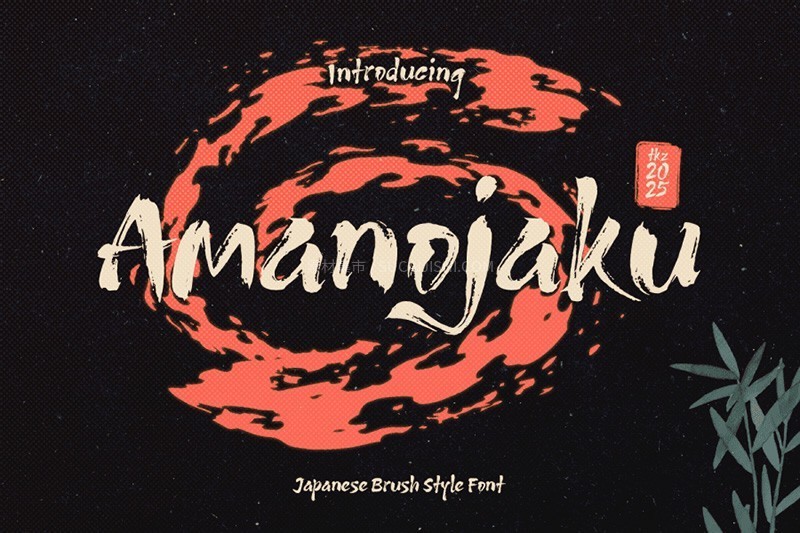
Zyukiharu
一款独特的日式书法风格英文字体。它将东方书法的流畅笔触和艺术感融入英文形态,为您的设计带来一种独特的视觉美感。
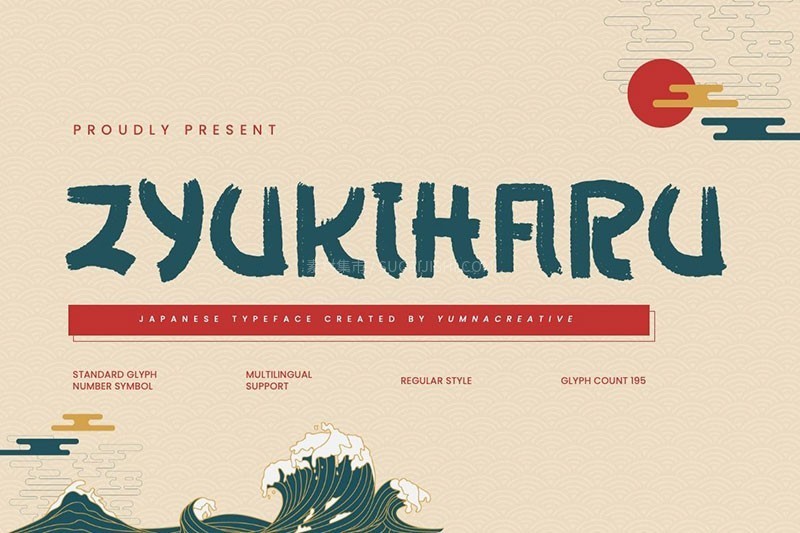
Kotaru
一款巧妙融合了时尚现代设计与传统日式美学的现代日式字体。它旨在打造多功能且易于阅读的排版体验。Kotaru 拥有三种独特的风格——常规、拉伸和轮廓,非常适合各种创意项目,例如徽标、品牌、邀请函、海报、标题、社交媒体等等。
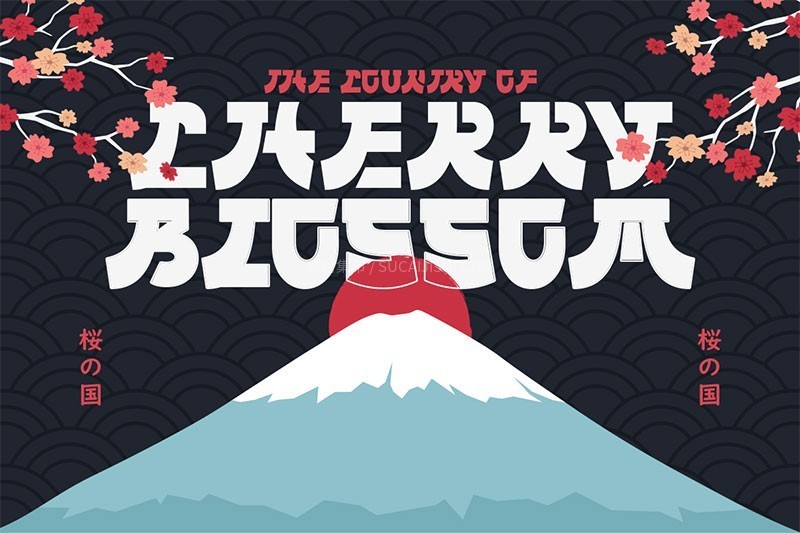
Osake
一款独具艺术价值的毛笔字体,笔触自然流畅,能为您的品牌、菜单、宣传品等增添 authentic(正宗)的日式韵味。
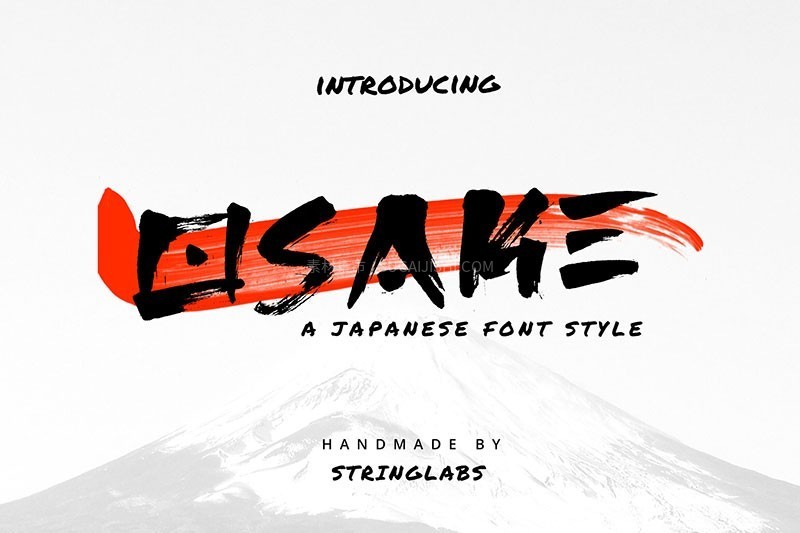
Yokai Game
一款厚重且粗犷醒目的日文字体,其灵感源自传统日式美学与大胆的当代设计。这种独特的融合使其非常适合用于游戏、动漫主题项目、漫画以及电子游戏标题。
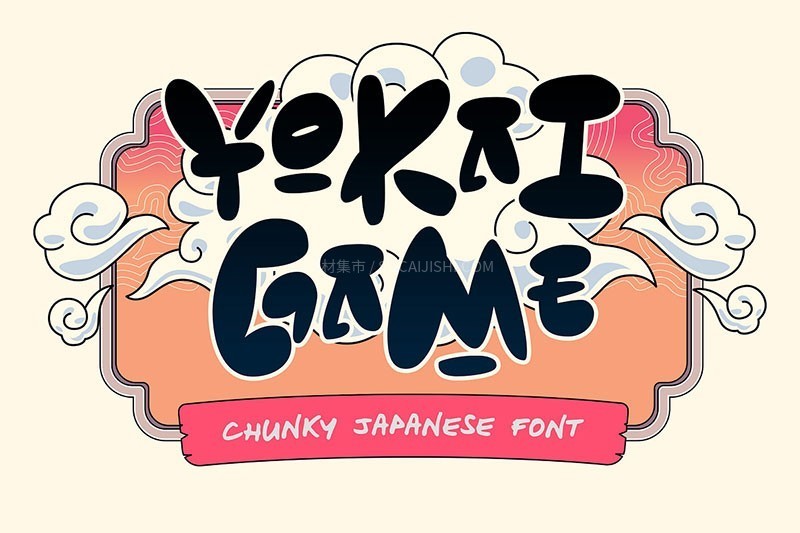
Kawara
一款融合了日式美学的英文字体,专为希望创作日语主题或亚洲风格项目的非日语用户打造。它能让您的标识、食品横幅、品牌形象、海报、电影/书名以及引言等内容更加华丽、强劲、醒目。
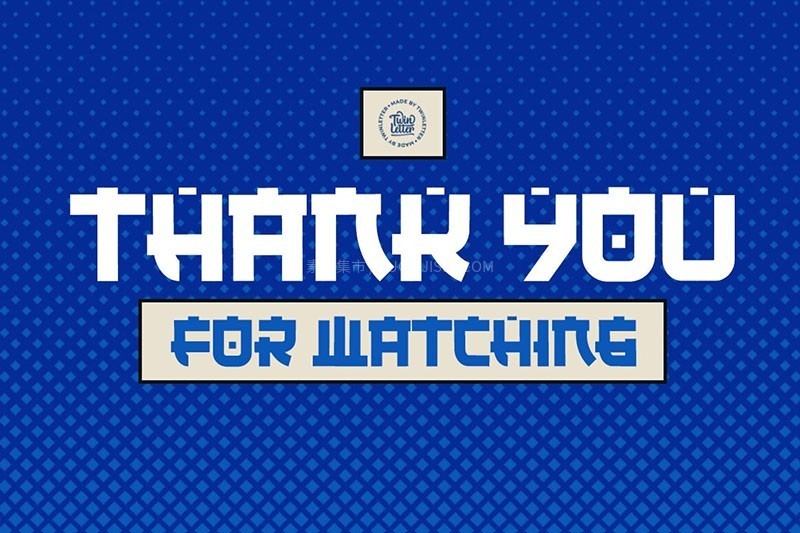
Hasabi
这款字体完美融合了传统韵味,捕捉了日本书法的精髓。适合用于品牌宣传资料、编辑排版、活动邀请函等艺术作品。
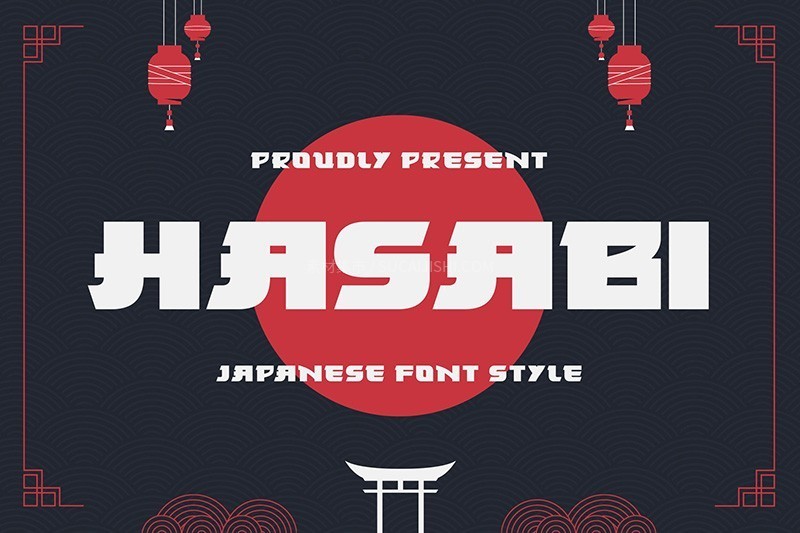
Kooshi
Kooshi 是一款充满活力的日式漫画字体,拥有粗体笔触和趣味十足的字符。它包含少量连字和替代笔触,为您的作品增添更多创意。
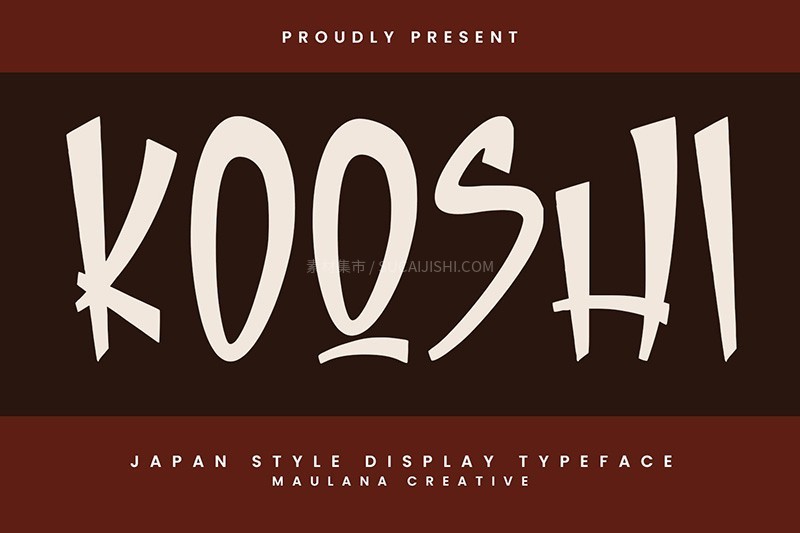
Bamida
一款日式主题的显示字体,它使用最自然的笔触和形态,创造出令人惊艳、自然、优雅的视觉呈现。
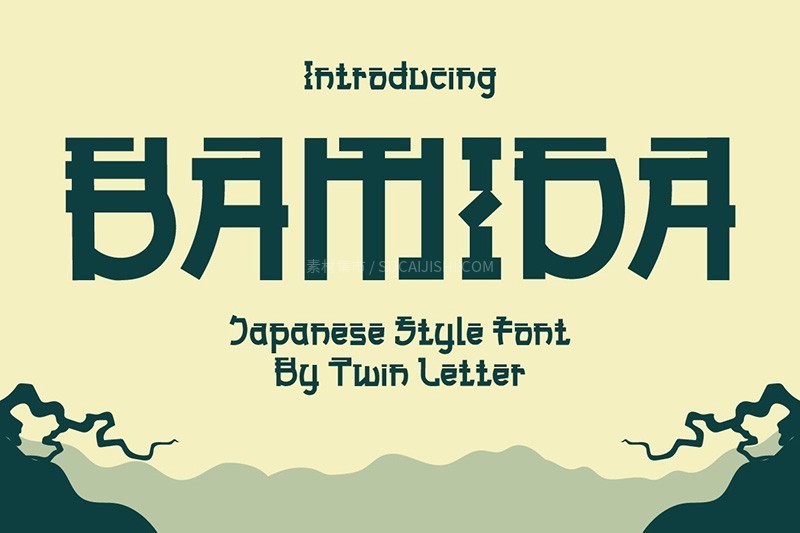
Nesuka
一款展现轻松活泼氛围的显示字体。它拥有比传统字体更自然、更独特的手写风格,能让你的项目显得充满乐趣和可爱。
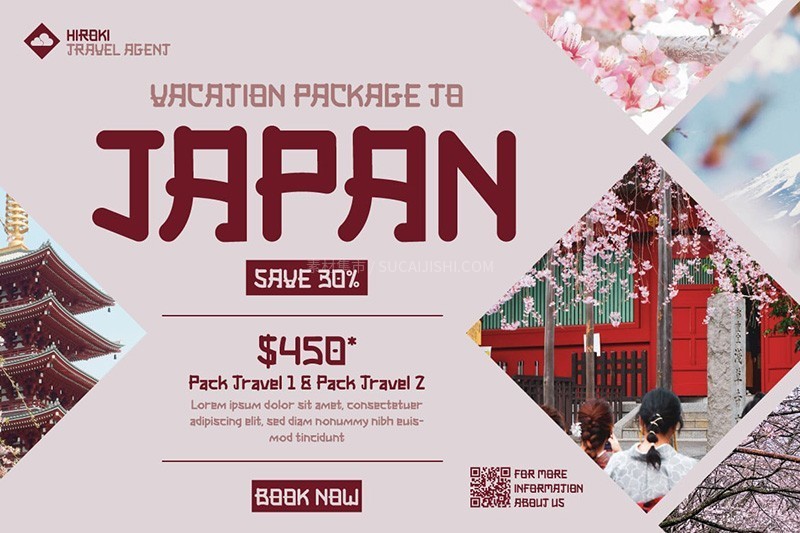
Aokahori
一款手刷风格字体,拥有流畅的毛笔笔触,充满艺术感。它非常适合用于任何标题、徽标、产品包装、品牌项目、杂志、社交媒体、婚礼,或仅用于背景上方的文字。
Samuri
一款融合了日式风格的字体,拥有异域风情和轻松随意的造型,极具吸引力,可完美契合您非凡的项目。